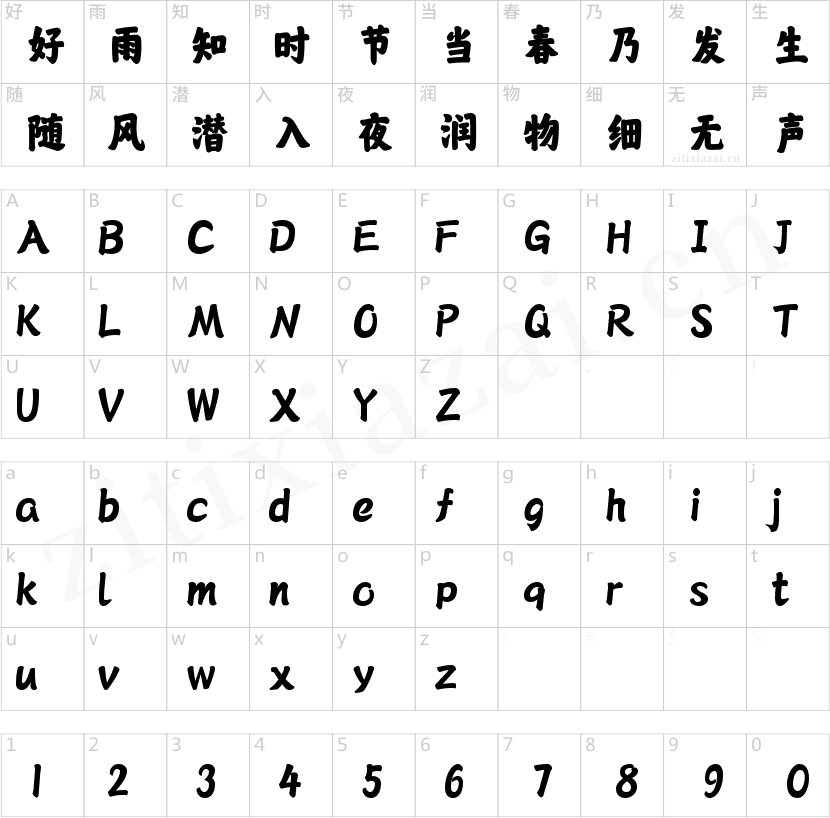
字魂1号-中国字魂
字体说明:字魂1号-中国字魂的设计灵感正是来源于榜书、匾额大字。在字魂1号-中国字魂的字形设计中,设计团队汲取传统匾额书法精髓,以现代化技术注入到设计过程里。传统匾额上的大字寄托了人们的祝福、歌颂、抒发壮志等美好情感,这些是字魂1号-中国字魂字形设计的“根”.字魂1号-中国字魂字体是由字魂创意字库设计并生产的一款可商用的字体,被收录于华夏王朝系列。该字体支持GB-2312标准,包含6943个中文、字母、符号和数字,字体类型偏向楷体,具有力量、豪放、中国风、帅气的风格,在市面上广泛用于视频影视、媒体&H5、晚会年会等场景。